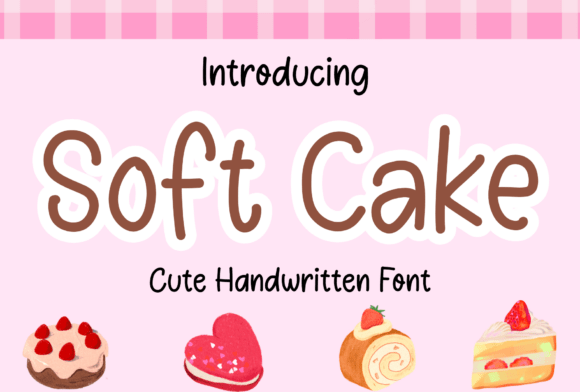
Soft Cake
หากคุณกำลังมองหาเนื้อหาคุณภาพสูงเช่น Soft Cake แพ็คเกจพรีเมียมนี้เป็นตัวเลือกที่ยอดเยี่ยมสำหรับโปรเจ็กต์สร้างสรรค์ของคุณ
สร้างขึ้นอย่างแม่นยำ Soft Cake ให้เวกเตอร์ที่สะอาด พิมพ์ตัวอักษรที่ราบรื่น และใบอนุญาตเชิงพาณิชย์เพื่อความสบายใจ